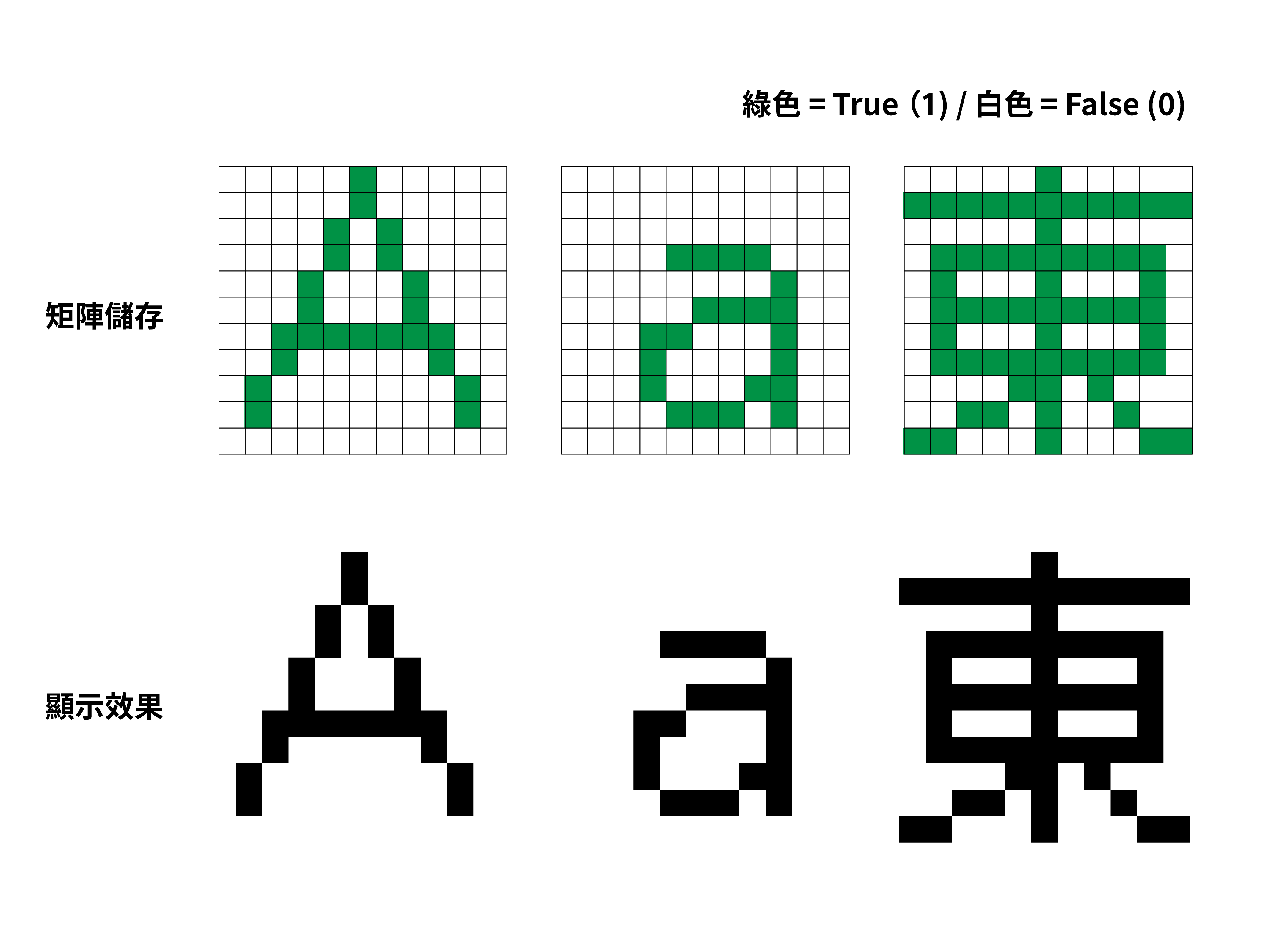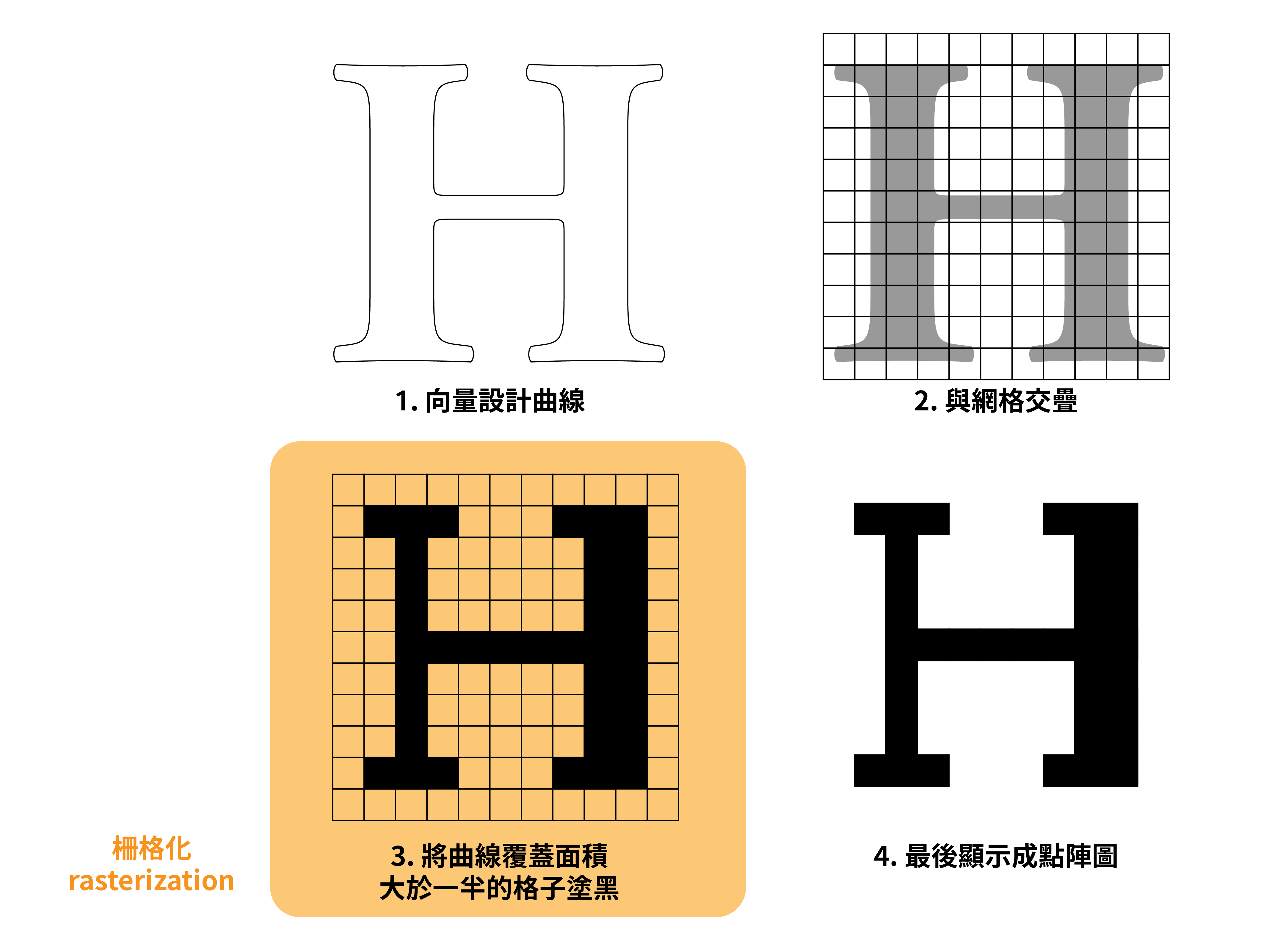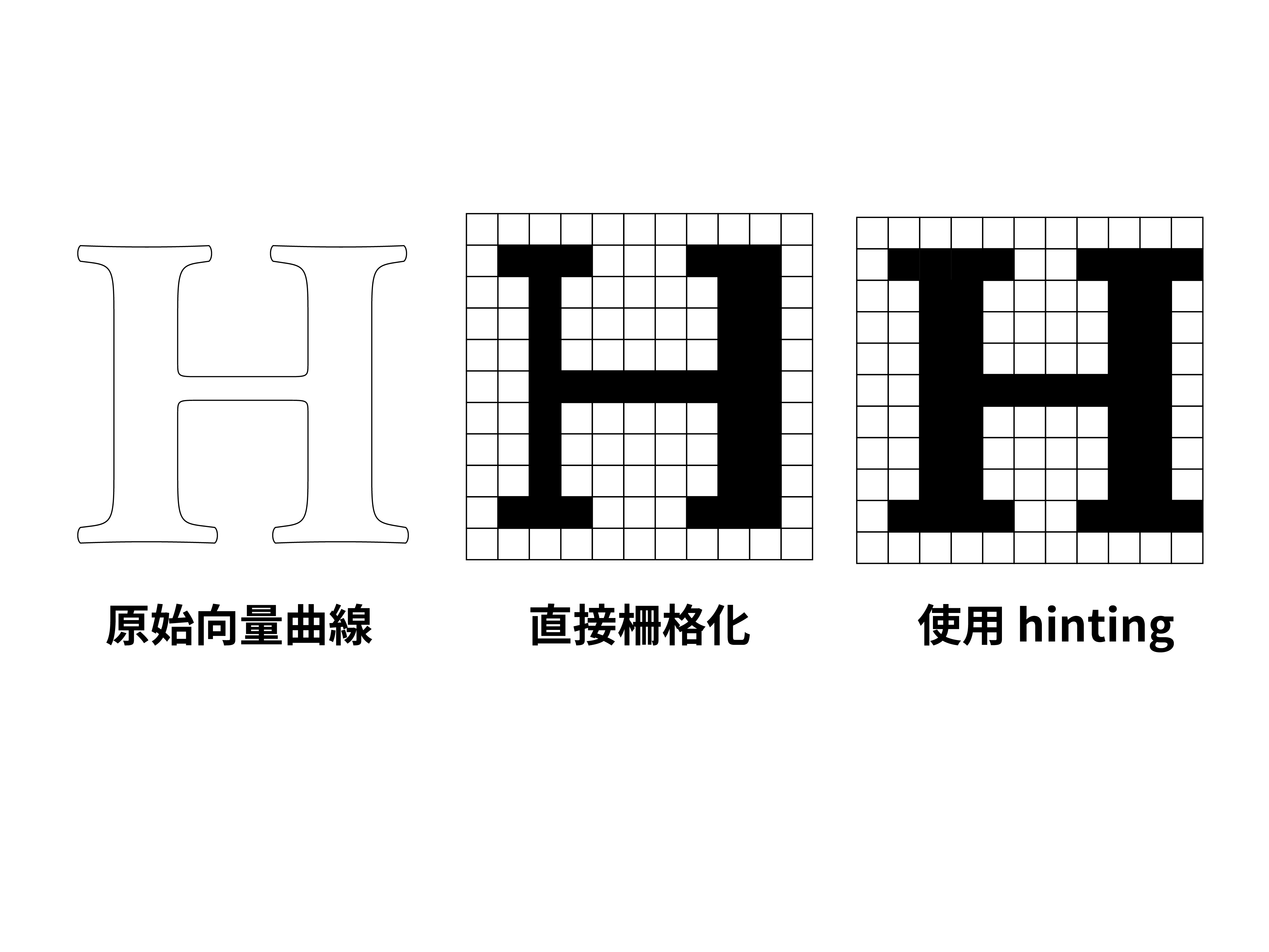
[Tech] 數位字型的歷史:從點陣字到 OpenType
早期的電腦——或者說計算機(computer)——是沒有終端(terminal)顯示器概念的,畢竟在那個使用打孔片作為輸入的年代裡,電腦處理的任務大多都是數值運算,其結果以類比的機械結構表示已經相當足夠。
直到 1964 年,IBM 2260 商用電腦上市,作為第一個擁有顯示終端的電腦,雖然其龐大的 CRT 螢幕只能顯示 6 行、每行 40 個,共 240 個字元,卻是計算機歷史上極具重要的突破,標示著人機互動新紀元的開始。
透過矩陣形式儲存點陣圖
伴隨著字元顯示的需求,數位字型的需求也隨之而來。
與現實字模裡的連續曲線不同,當時的顯示器分辨率極為有限,字符的輪廓多以矩陣的形式儲存,工程師在有限的網格空間內,將黑色需要顯示的部分被標示為 1、留白的部分則被標示為 0——以一個僅有 0 與 1 的矩陣紀錄,電腦再控制其像素(pixel)的顯示與否。
透過這種點陣圖(bitmap)形式儲存的字型,雖然可以顯示,但比起人工雕鑄的字模來說,其凹凸不齊、就像被啃過一樣的邊緣實在是相當的醜陋。而且如果遇到字符需要縮放的時候(尤其是放大),這種鋸齒狀的邊緣就會越來越明顯。
Ikarus 與 Metafont 的嘗試
想要製作一套看起來「滑順」的字型,比起用格子去儲存外框曲線,我們需要一種新的方式。
1972 年,Peter Karow 發表了 Ikarus 字型軟體(德文拼法的「伊卡洛斯」,就是那個飛太高、太靠近太陽,翅膀融化掉到海裡的伊卡洛斯),使用者可以透過樣條函數(spline)來標記直線與曲線,藉此繪製漂亮的輪廓。
1979 年,Donald Knuth(高德納,就是發明 TeX 的那個神人)在開發 TeX 時,有感於當時的字型品質實在不適合排版,另外編寫了 Metafont 字型描述語言,讓工程師可以透過三次樣條插值(Cubic Hermite spline)來描述曲線的外觀。
以下面這個水餃圖形為例,若要以 Metafont 描述,則需要使用以下的咒語:
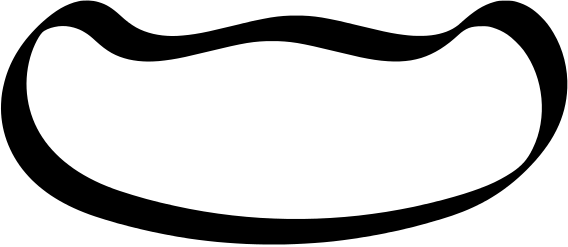
%file name: beta.mf
%mode_setup;
% Define a beanlike shape for the character B
beginchar("B",11pt#,11pt#,0);
% Setup coordinates as an equation system
y1=y2=y3=0;
y4=y5=y6=h;
x1=x4=0;
x2=x5=w;
x3=x6=2*w;
% Define pen
pickup pencircle xscaled 0.2w yscaled 0.04w rotated 45;
% Draw the character curve
% z1 is the same as (x1, y1)
draw z1..z3..z6{z2-z6}..z5..{z4-z2}z4..cycle;
endchar;
end
嗯哼…?
毫不意外的,Metafont 字型描述語言完全沒有流行起來,畢竟在畫出一條線之前,必須要學會如何建構數學方程式——這個門檻連高德納自己都承認「有點難」。
向量轉點陣
Ikarus 與 Metafont 都使用數學方程式的形式來描述曲線,但曲線要怎麼轉成顯示器上的網格呢?
最簡單的方法就是將網格和曲線鋪在同一張紙上,如果曲線塗黑的部分(也就是字本身)超過一半面積以上,則將該格子塗黑;反之則留白,如此一來,所有的曲線就能透過柵格化(rasterization,或譯成光柵化)的方式轉成螢幕能顯示的格式。
不過,柵格化的邏輯雖然簡單,但顯示的效果就跟圖片顯示的一樣,實在是差強人意。
Adobe PostScript
1970 到 1980 年代堪稱是計算機的戰國時代,性能不斷提升的商業電腦取代了笨重的打字機,螢幕與鍵盤成為了辦公室的日常風景之一。
當時還沒有「所見即所得」(WYSIWYG)的概念,使用者在電腦上面看到的文字,會在印表機端重新渲染(render),與實際印出的字型常常是不一樣的;而每台電腦與印表機都有自己的文件規格,不同廠商之間的是無法通用印表機的。總而言之,雖然已經可以透過電腦列印文件,但檔案的相容性依舊是個大問題。
有鑑於此,當時在 Xerox 工作的 John Warnock 和 Chuck Geschke 便有了一個大膽的想法——Interpress 計畫,他們打算發明一種新的印刷描述語言一統天下,打破既有的廠牌壁壘,讓文件不再挑印表機,達到真正的通用。
想當然爾,Xerox 和其他廠商都對該計畫興致缺缺,無論是市占率還是技術,都沒有一個強烈的動機讓他們願意放棄既有的標準保護。但儘管如此,John Warnock 和 Chuck Geschke 還是對 Interpress 計畫有信心,在 1982 年,他們離開 Xerox 創業,將 Interpress 將一步擴充成 PostScript 標準,而公司的名字則以 Warnock 家裡附近一條河流命名——Adobe 成立了。
1984 年,Adobe PostScript 語言正式問世;隔年,Apple 在與 Adobe 合作下發表了第一台使用 PostScript 語言的印表機 LaserWriter,引發了桌面出版(Desktop publishing)的革命。
PostScript 有許多極為領先想法,深深影響了後來的字型格式。舉例來說,為了解決上面所提到在柵格化問題,PostScript 允許每個字符紀錄 Hinting 訊息(可以想成是一個小抄),可以告訴渲染器哪部分的字幹(stem)尺寸要一致(例如 H 的兩個豎筆寬度應該要一樣)、高度應該要保持多高,而不至於歪掉。
可以說,字符由過去單純被動的被柵格化,變成可以主動要求柵格化時要保留的資訊,大大提升了的字型顯示品質。
最重要的是,比起 Ikarus 和 Metafont 透過樣條曲線來描述曲線的形狀,PostScript 引入了貝茲曲線(Bézier curve)。和前兩者相比,基於 de Casteljau 演算法的貝茲曲線只要「拉動」控制點就可以畫出想要的曲線,不僅直觀、易控制、容易進行升階與降階、其計算也更加的快速。也因此,PostScript 標準在很短的時間內便成為了主流。
起初,PostScript 定義了多種規格——其中又以 Type 1 與 Type 3 字型最常見。前者可以免費使用,後者則需要向 Adobe 購買授權。Type 3 雖然完全支援 PostScript 的功能,但 Adobe 卻故意 (現在來看就不怎麼意外) 讓 Type 3 無法支援 Hinting,使得 Type 3 字型在處理小尺寸字型的時候依舊無法很好的被柵格化,使用 Type 3 字型列印出來的品質也只能說相當普通。
若想要使用支援 Hinting 的 Type 1,不僅需要向 Adobe 高額的授權費,還僅能在經授權的 PostScript 印表機上列印。此外,Adobe 還委託許多設計師設計 Type 1 字型,使得市場上高品質的字型幾乎都是 Type 1 格式,反過來壟斷了高階字型的印刷市場。
雖然第三方字型廠商(例如 MonoType)對於 Adobe 壟斷更好的 Type 1 字型一事感到無語 (搞差別待遇可謂是 Adobe 的基因),但 PostScript 還是在市場上取得了極大的成功——畢竟,貝茲曲線的繪製簡單許多,而且現在至少可以販售 Type 3 的字型了。
從 TrueType 到 OpenType
當時,作為作業系統的龍頭,Microsoft 和 Apple 都被迫與 Adobe 合作,以確保用戶願意使用他們的作業系統來進行文字的處理;而在另一方面,兩間公司對於所見即所得軟體的興趣也日益增高,不停的向 Adobe 打聽 Type 1 的渲染技術。然而,Adobe 對 Type 1 悉心保護的態度,使得雙方都無法真正進入到 PostScript 的開發與規格制定過程。
1987 年,受不了 Adobe 的 MicroSoft 和 Apple 決定攜手合作,發布 TrueType 格式的字型規格,並從 System 7(後來常被稱作 Mac OS 7)與 Windows 3.1 開始支援,全面推廣。儘管 Adobe 將 Type 1 字型瞄準在高階專業印刷領域,但在商用及個人電腦市場不斷擴張的情況下,TrueType 字型很快地取代 PostScript 字型,成為市場主流。
不過,Apple 的野心不僅僅止步於此,他們在原本 TrueType 的基礎上越走越遠,擴充出 TrueType GX 與 Apple Advanced Typography (AAT) 格式的字型。雖然他們從未成為主流,但其包含了許多有趣的字型功能,例如可自由開啟關閉的連字、上下文替換、替代字形與文體集,都影響了後來 OpenType 特性的開發。
1997 年,也許是 Adobe 終於願意認輸,也許是受到 Apple 野心的刺激,Microsoft 與 Adobe 握手言和,致力於開發 TrueType 次世代版本,並將其稱為 TrueType Open,也就是後來的 OpenType。OpenType 不僅向下兼容 TrueType 與 PostScript,在多次版本迭代中,也吸收了過去 PostScript、TrueType、AAT 的優點,反映在其擁有的特性(feature)上。
從 1999 年 Adobe 宣告不再生產 Type 1 字型,並逐步將原有的 Type 1 字型重新封裝為 OpenType 格式開始,OpenType 的市佔率不斷攀升。2021 年,隨著 Adobe 正式宣佈旗下的 InDesign、Illustrator、PhotoShop 停止支援 Type 1,PostScript 時代迎來他的終結,OpenType 格式已經成為目前字型與印刷產業事實上的(de facto)標準。